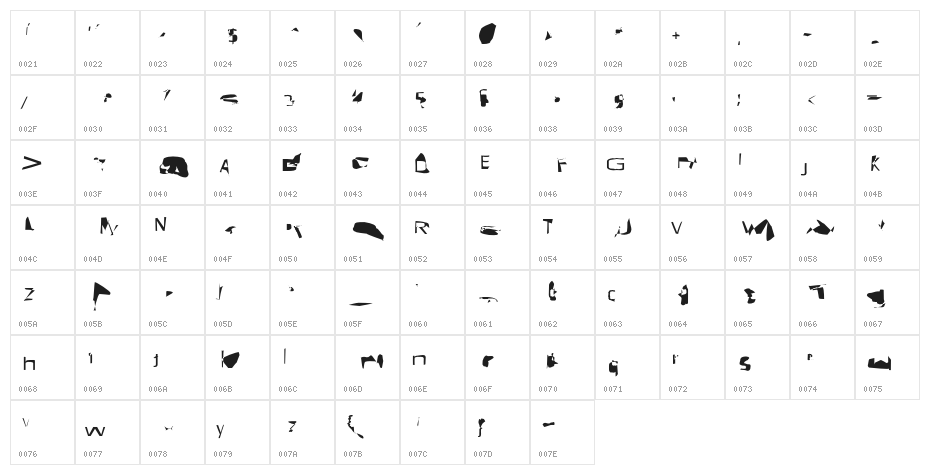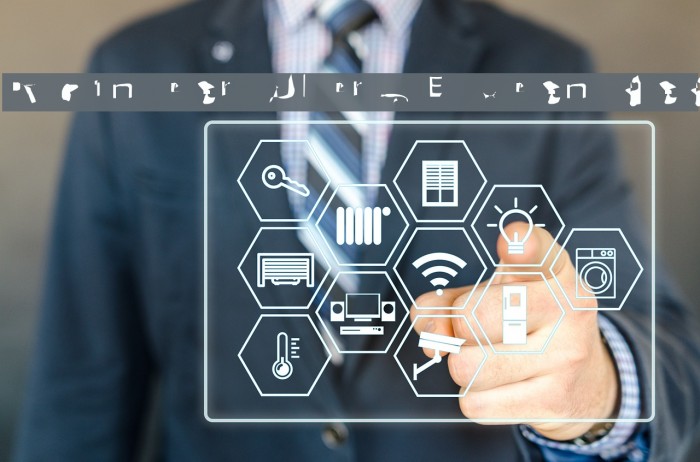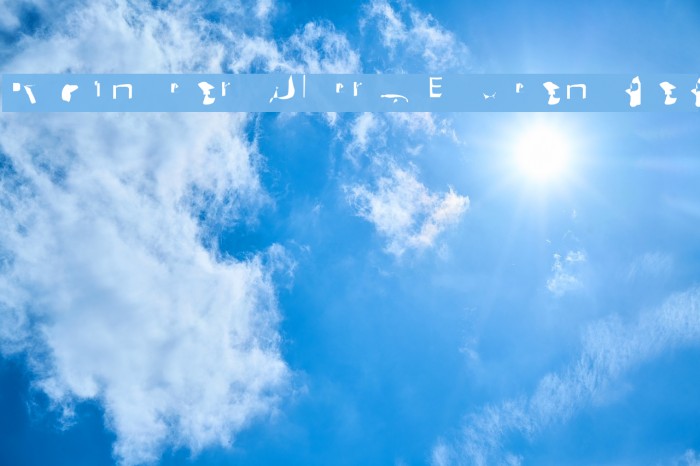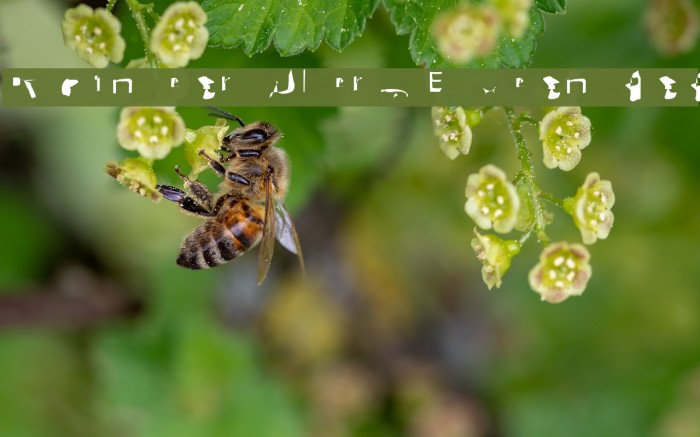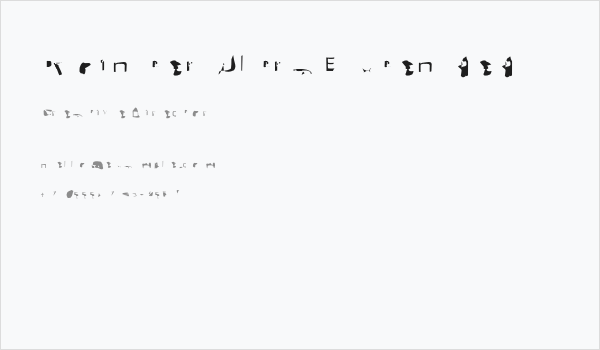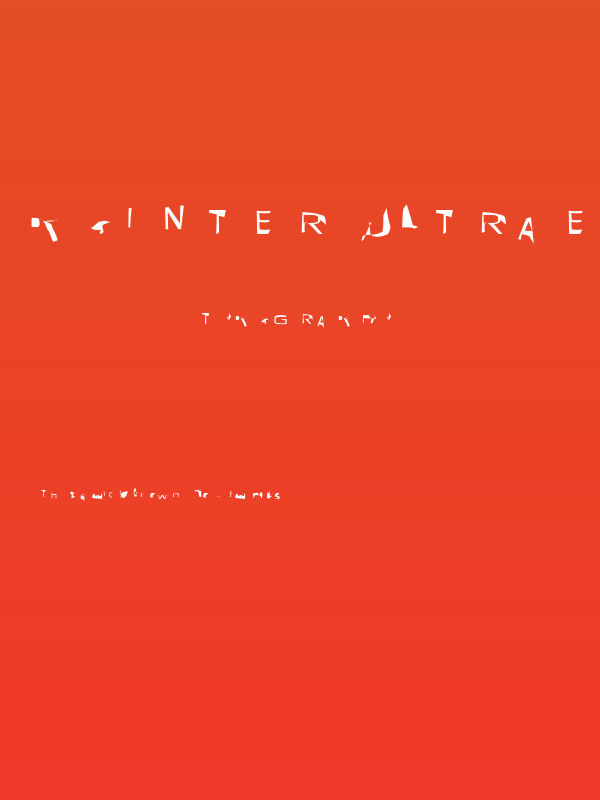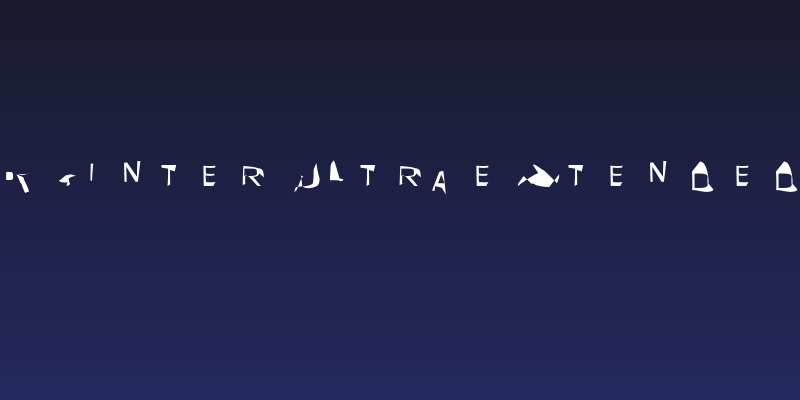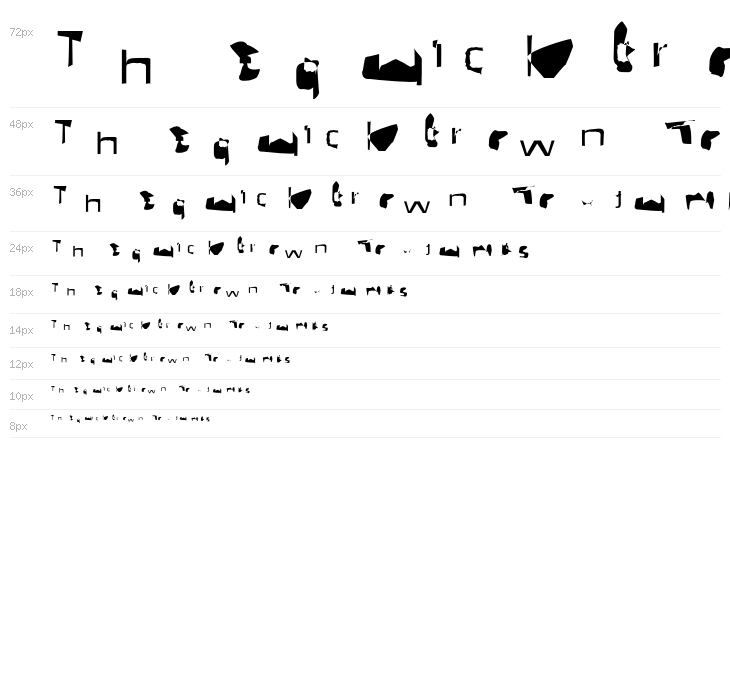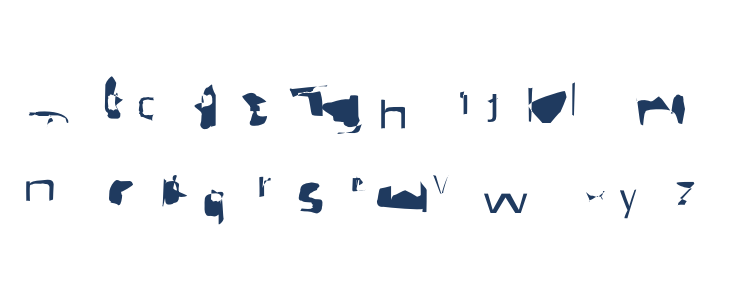
Pointer UltraExtended Font
✎ Distorted Eroded
| العرض | Expanded |
| النمط العام | Modern, Abstract |
| حالة الاستخدام | Logos, Posters, Album Covers |
| مشاريع مقترحة | Ideal for experimental art projects, avant-garde posters, album covers, and digital media where a bold, unconventional look is desired. |